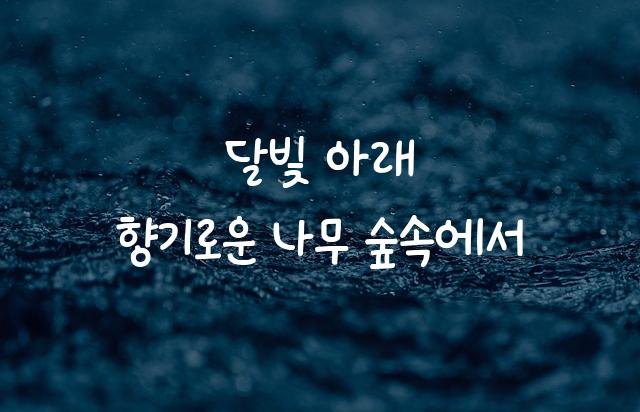
국립공원 꼬미 폰트는 국립공원공단에서 제작한 사랑스럽고 귀여운 디자인의 폰트입니다. 또박또박하고 명확한 글자 형태로 읽기 쉬움과 동시에 친근한 감성을 전달합니다.
국립공원 꼬미은(는)
귀여운 스타일 계열의 생김새를 가지고 있으며
어린이 책, 초대장, 인사말 카드 등에서 자주 활용되며, 효과적인 메시지 전달에 적합합니다.
이 폰트는 라이프스타일, 유아/가족, 환경/에너지 분야에 잘 어울리며,
귀여운, 편안한, 자연스러운 느낌을 담고 있는 것이 특징입니다.